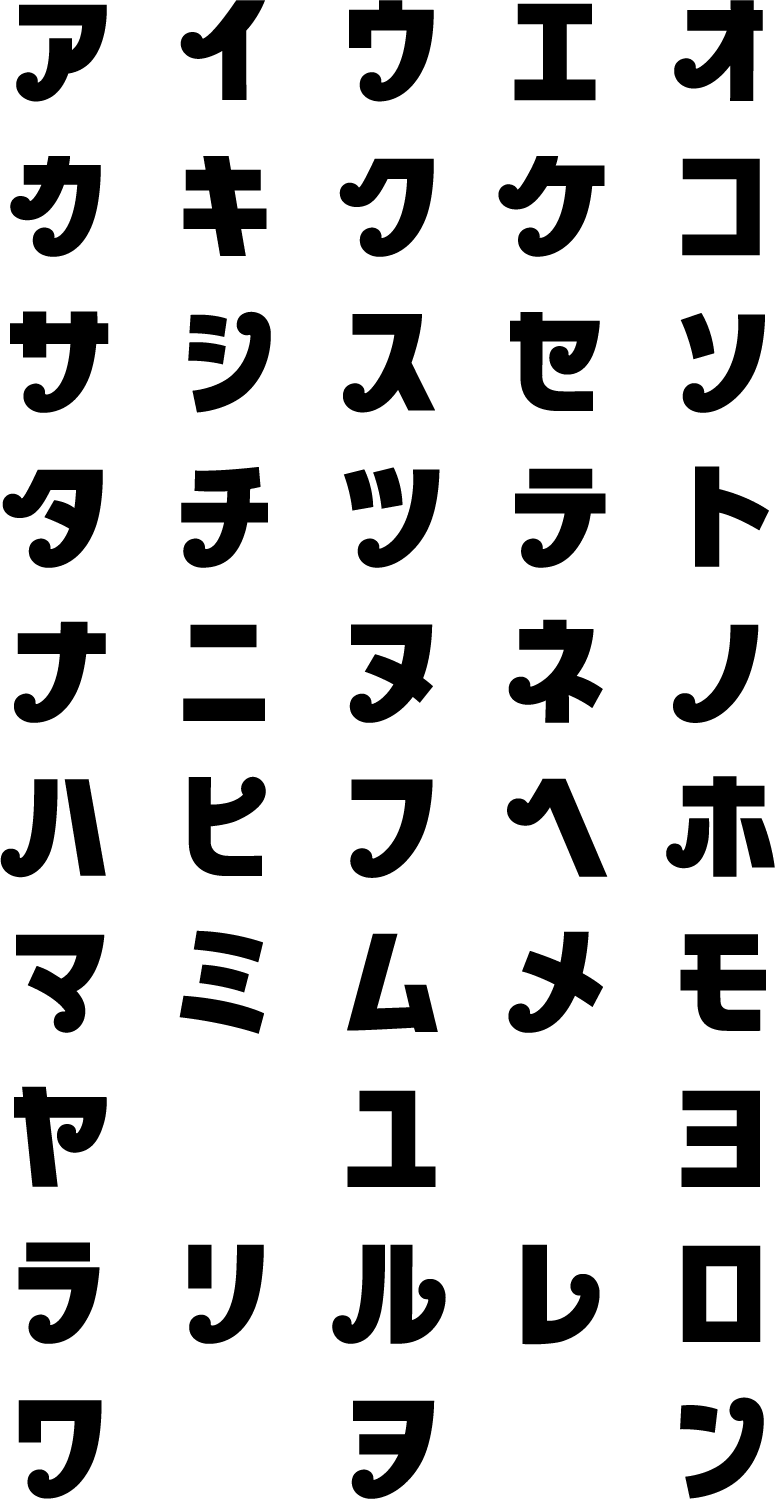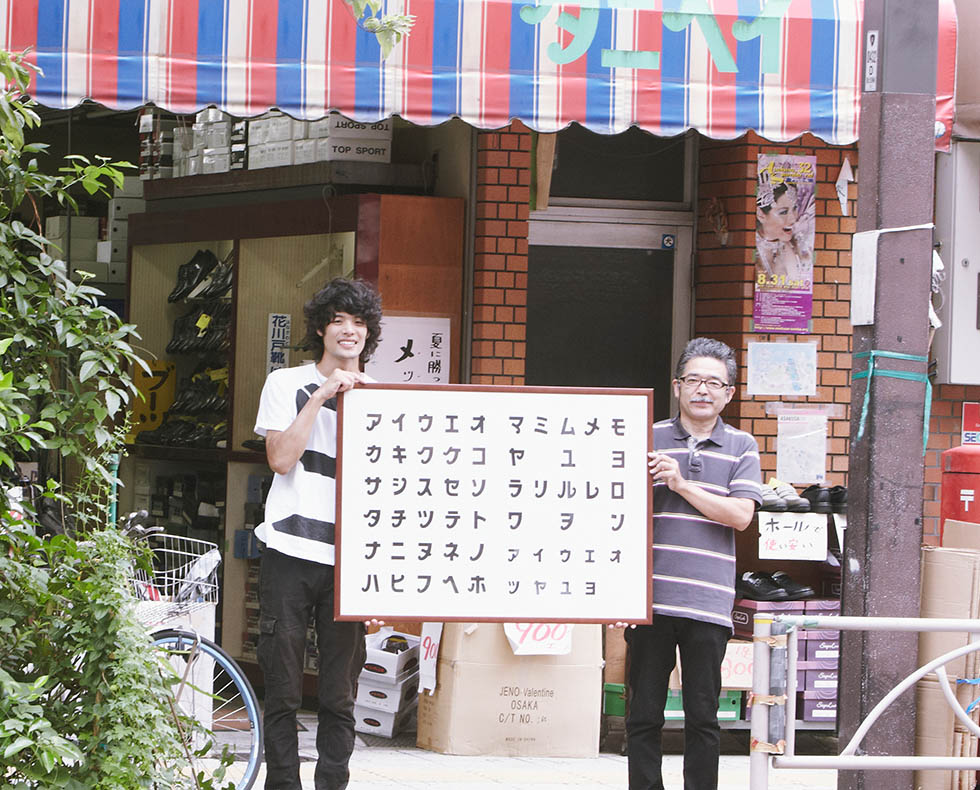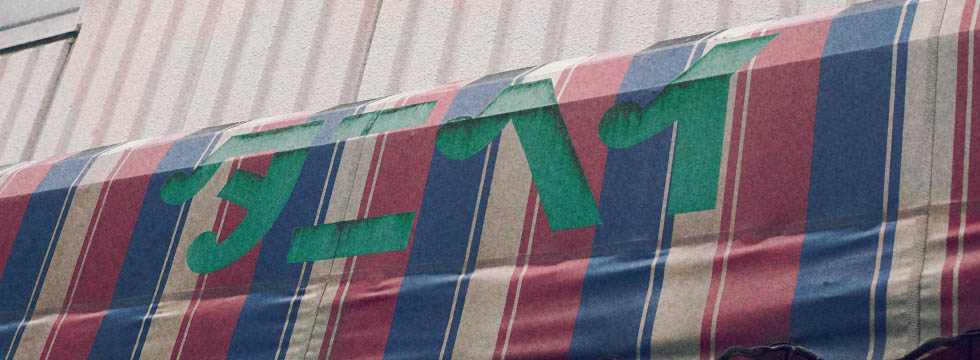
視線が文字の中にある丸みに、ゆるゆると吸い込まれていく…。この魅惑的な丸い膨らみが、この書体にキッチュな脱力感を与えているのである。
「タニヘイ」は、もとは明治時代に草履や下駄を作る製造業から始まった。創業者の谷崎平吉さんの「谷」と「平」を組合せた屋号である。履物業界ではそう言った名前の付け方が慣習としてあるのだと、三代目で現店主の谷崎清一郎は語る。「靴屋だから、わかりやすくしといたほうがいい。谷平の平の字がさ、タニヒラって間違えられるのやじゃん。だからタニヘイってカタカナなのよ。」今使っている書体は、初代の平吉さんが看板屋さんにお願いしてつくったアルファベットの「tanihei」を参考にしたそうで金看板に刷って残してあったものを見本にカタカナを作成したそう。「亡くなった初代は西洋かぶれだったの。で、早く亡くなってる。昭和45、6年に亡くなってるから、余計愛着が深い。なんか残ってないとやだね、ってことで。」
“TANIHEI” originally started out as a manufacturer of sandals and Geta (Japanese clogs) in the Meiji era (1868-1912). The name is a combination of “Ta-Ni” and “Hi-Ra” of Mr. Heikichi Tanizaki as Japanese name, the founder of the company. Mr. Seiichiro Tanizaki, the third-generation and current owner of the shop, said that “It is customary in the footwear industry to use such a name. We are a shoemaker, so it is better to make the name easy to understand. The character for Ta-Ni-Hey could be mistaken for Ta-Ni-Hi-Ra. That’s why we use Katakana.” The typeface used today is based on the alphabet “tanihei” which the first-generation Mr. Heikichi asked a signboard shop to create for them, and the Katakana was created using a sample that was printed on a gold signboard and left behind. “Owner of the first generation, who passed away, loved the culture of the West, and he died early. He died in 1970 or 1971. So I have a deep attachment to him. I felt it would be a shame if there was nothing left about him.”